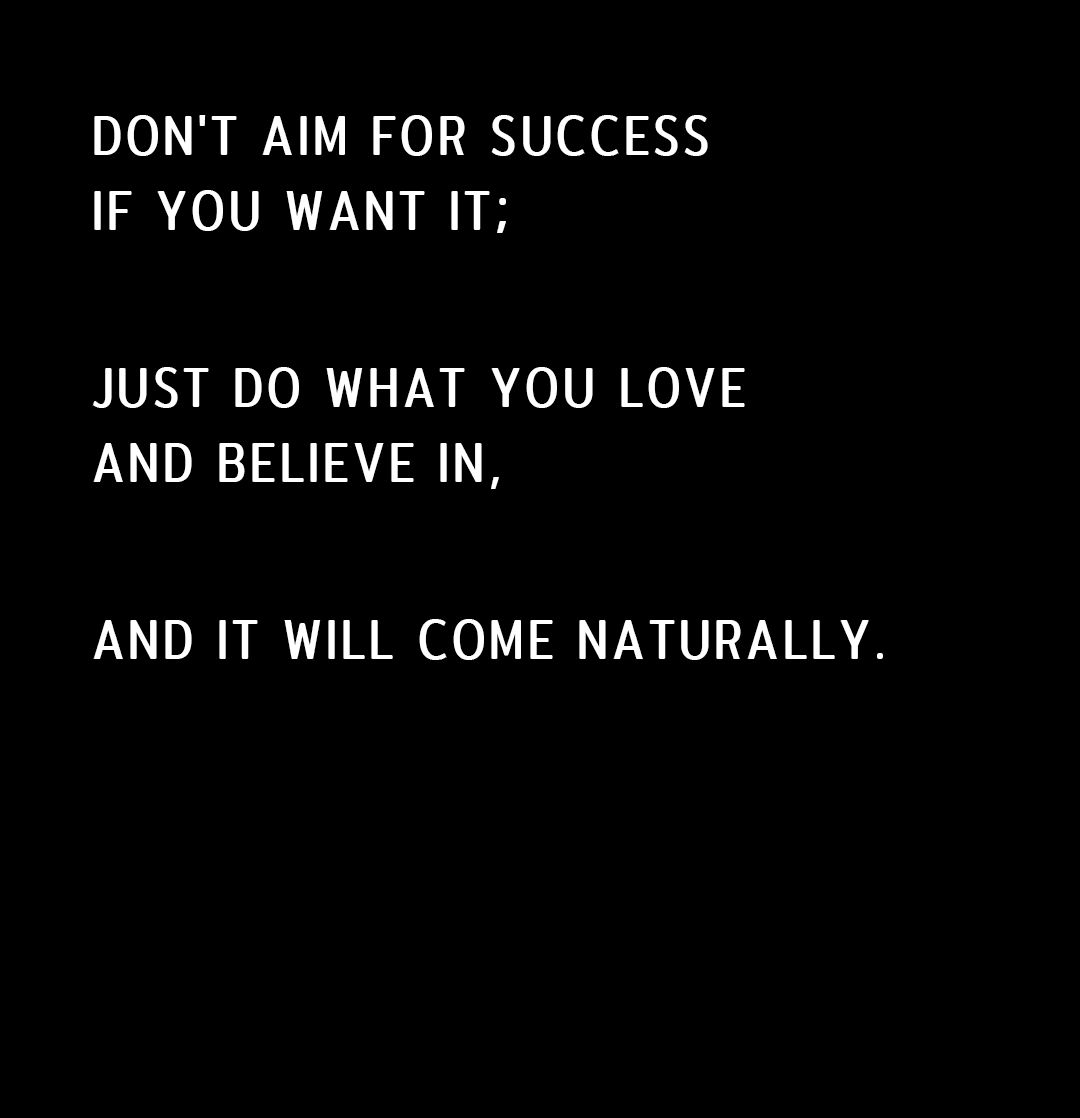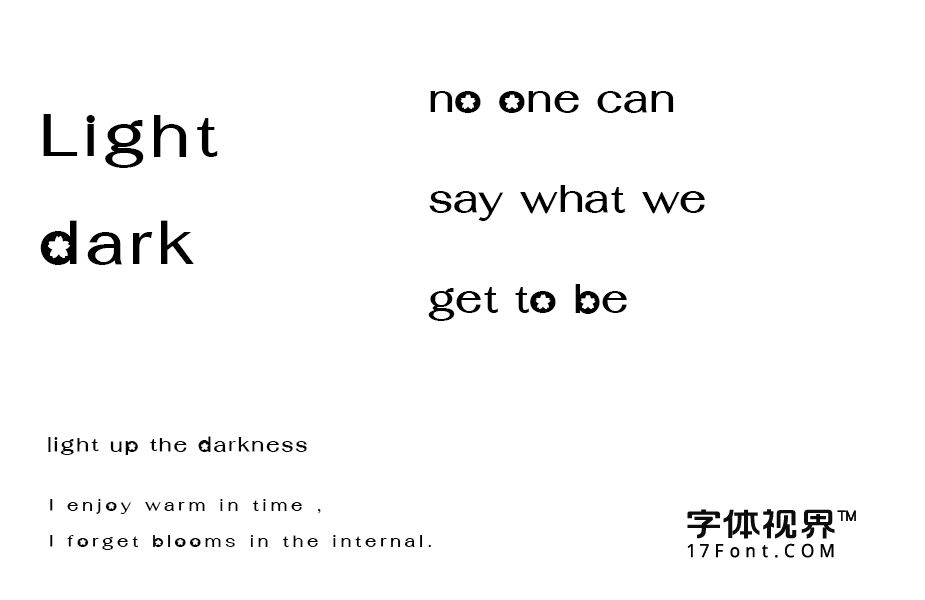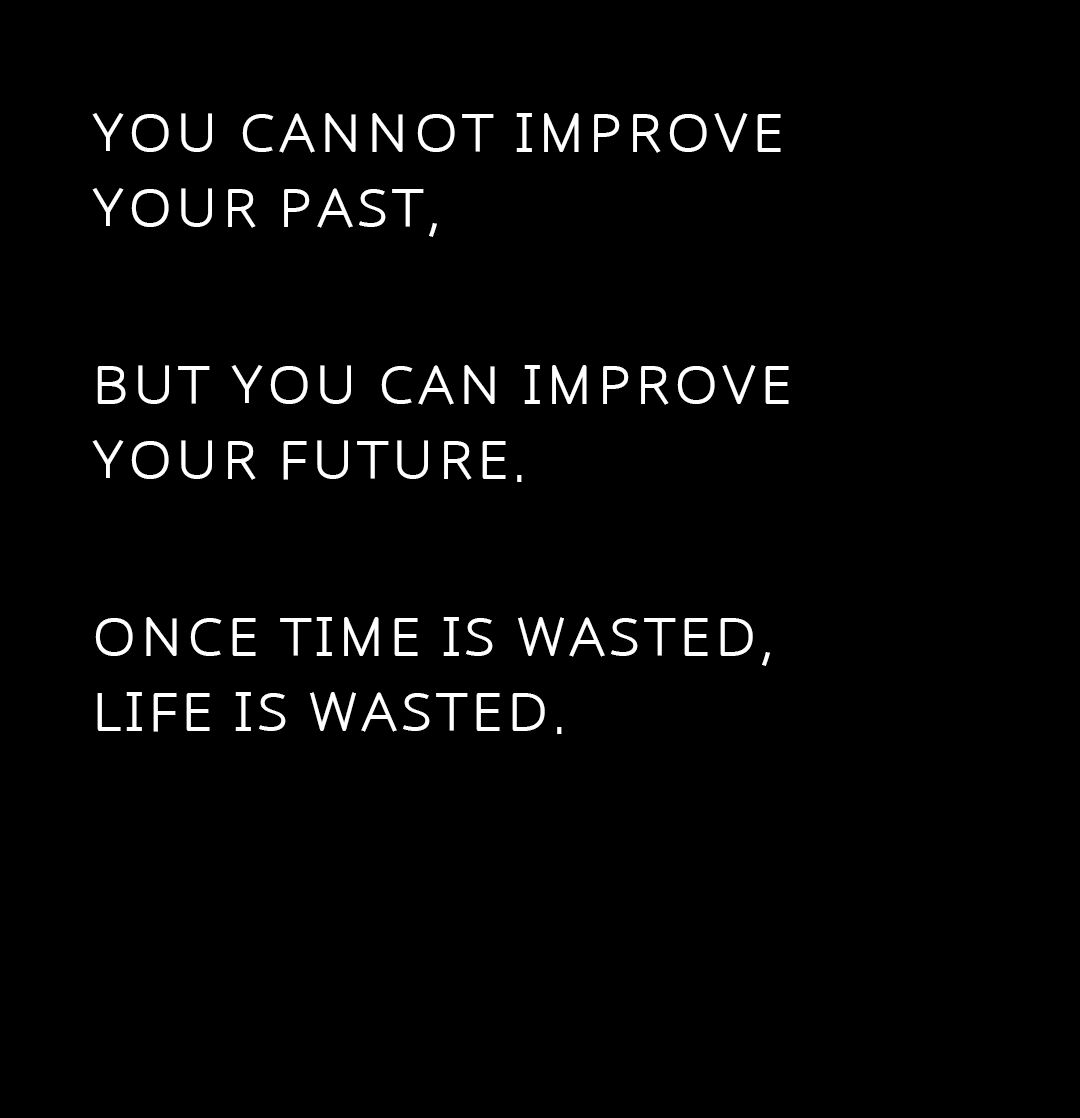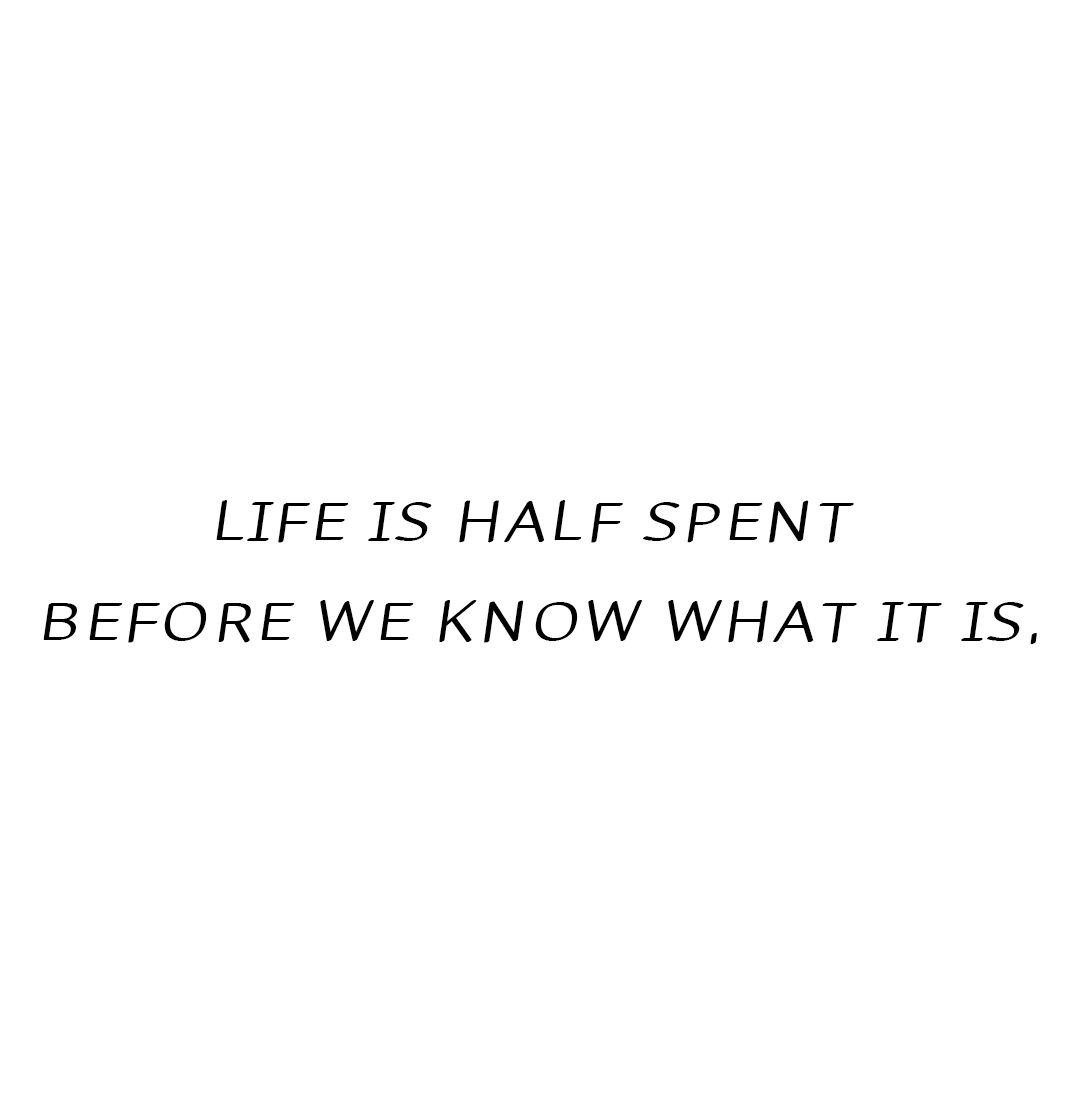
HyFont字库入驻字体视界
与“粽”不童,在儿童节邂逅端午节之际,字体视界平台又新增了一个字体合作伙伴-HyFont字库。
HyFont字库作为国内西文字体的先行者、实践者,可提供专业定制服务来满足客户需求。
西文字体在设计中也是不可缺少的一个元素,我们在设计的过程中,难免会遇到缺少文案或者是文案较少的情况,这时候西文字就显得尤为重要了,我们可以在文案中增加一些有特色的西文字来修饰,让画面更丰富、更有层次。
目前,第一波西文系列字体,HyFont字库一共上线了10 款。我们先来欣赏部分作品。
HFAppleTree
HFHaru
HFBerry
HFHockey